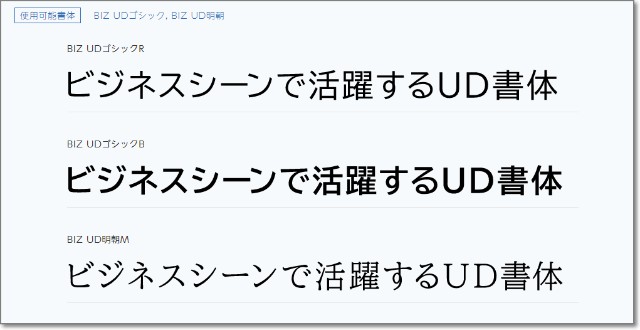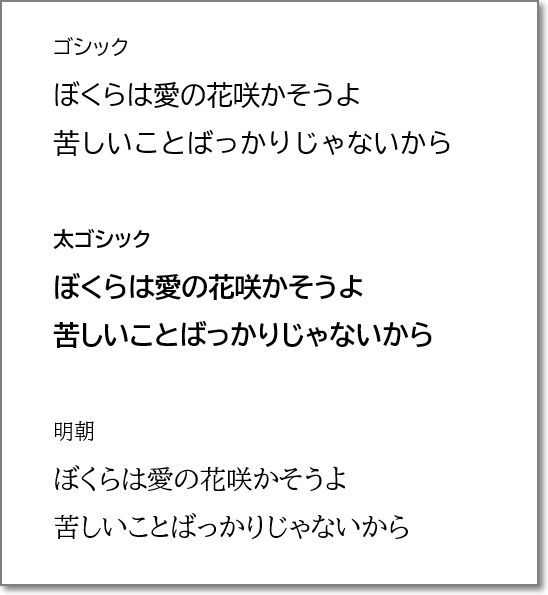
モリサワの、ユニバーサルデザインフォント。
「BIZ UDフォント」
MS明朝やMSゴシックに不満があって、
「もっと見やすいフォントを使いたい」と感じているかたには、オススメ。
・BIZ UDゴシックR=ゴシック体
・BIZ UDゴシックB=太ゴシック体
・BIZ UD明朝M=明朝体
それぞれ、プロポーショナルと等幅の、2種類が用意されています。